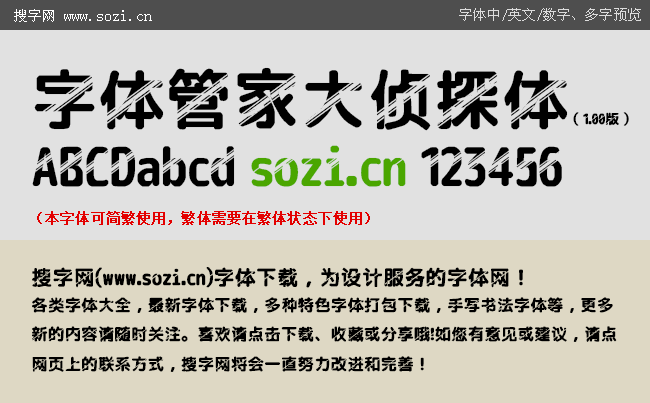
字體管家大偵探體
搜字網(wǎng)給大家提供一款字體管家大偵探體中文字體下載。這款字體是以粗圓字體為原形,字體間加入了玻璃反光的效果圖案。在具備粗圓字體清晰醒目風(fēng)格的同時,也增添了趣味性,是一款非?蓯鄣目ㄍㄗ煮w,適合兒童書刊、商品包裝、海報設(shè)計等廣告設(shè)計場合使用。